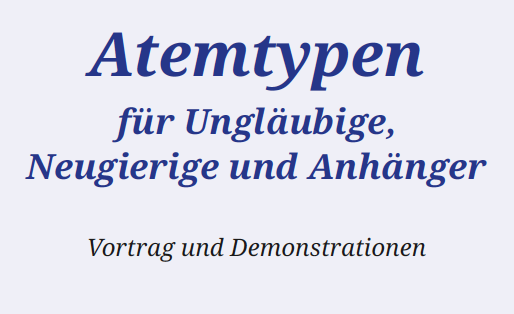
Was fällt euch spontan zu Gesang, Atemtechnik, Singstimme ein?
Luft: dünne, feine Striche, aber nicht zu spakelig :-?
virtuos, aber nicht zu verspielt :-?
Ich muss spontan an Rhethorik denken. Also alte Lateiner. Also Trajan oder Optima oder sowas in der Art. Ich unterstelle Dir mal, dass Du eine Wortmarke bilden möchtest und deswegen eine Displayschrift benötigst. Da sieht folgende recht luftig aus: https://www.myfonts.com/fonts/wilton/cyan/
weniger schriftbezogen assoziiere ich:
• Tonleitern
• mehr oder weniger lächerliche Stimmübungen beim Einsingen
(„mo-lo-mo-lo-mo-lo-tooooooo“ oder „bi-ba-bu-bi-bi-bi-buuuuu“ oder so)
• zur Atemtechnik: mit Korken im Mund sprechen, beim Kopfschütteln sprechen,…
• unter der Dusche singen/mit zugehaltenen Ohren singen
• mehr weiß ich grad nicht, kann aber – wenn gewünscht – gerne noch weiter überlegen und dann ergänzen)
... das Bass mehr Bums hat als schriller Sopran, und dazwischen gibts Abstufungen wie bei gut ausgebauten Schriften mit vielen Schnitten ...
fällt mir dazu ein.
Ich muss spontan an Rhethorik denken. Also alte Lateiner. Also Trajan oder Optima oder sowas in der Art. Ich unterstelle Dir mal, dass Du eine Wortmarke bilden möchtest und deswegen eine Displayschrift benötigst. Da sieht folgende recht luftig aus: https://www.myfonts.com/fonts/wilton/cyan/
Das passt auch zu meiner Assoziation, bis auf die rhetorischen Lateiner :-)
Als Musiker bei Atemtechnik: solide Grundlage. Ohne solide Stütze und Atmung wird es auch mit der Singstimme nix. Atemtechnik erfordert viel Übung und Muskulatur, da darf nix flimsiges her.
Ganz spontan fiel mir als erstes die Vollkorn ein. Tägliches Brot, solide Grundlage und sehr robust. Die Singstimme kommt dann mit viel Beweglichkeit und Leichtigkeit "oben drauf". *grins*
… Ganz spontan fiel mir als erstes die Vollkorn ein. …
:hammer::gimmifive: Genau diese kam zuerst zum Einsatz, passte nach meinem Geschmack auch gut. Kräftig und leicht zugleich. Die Bold war dann aber doch ein wenig zu fett, wir sind auf die Droid umgeschwenkt. Da ist die Bold nicht ganz so fett und die Kursive ist schön weich und rund und locker.
Was meint ihr?
Meinen persönlichen Geschmack trifft es nicht, ich finde es gibt schöneres als die Droid, aber das ist meine ganz persönliche Meinung (und natürlich verstehe ich das mit dem fetten Schnitt der Vollkorn). Die Droid ist aber eines mit Sicherheit nicht: klischeebeladen. Sie vermittelt schon die Robustheit die ich angesprochen habe. Von daher kann ich mit der Lösung sehr gut leben. :gimmifive:
Das schwungvolle y gefällt mir gut. Ansonsten fehlte mir bei der Droid etwas der eigenständige „Esprit“ (ist eben inzwischen auch eine der strapazierteren Schriften). Falls vorhanden könnte ich mir deshalb auch gut Folgende vorstellen: FF Milo Serif (hier Medium) Italic (enthält auch das komplexe g als Alternative).
(Corda, Pollen, Fertigo, …)